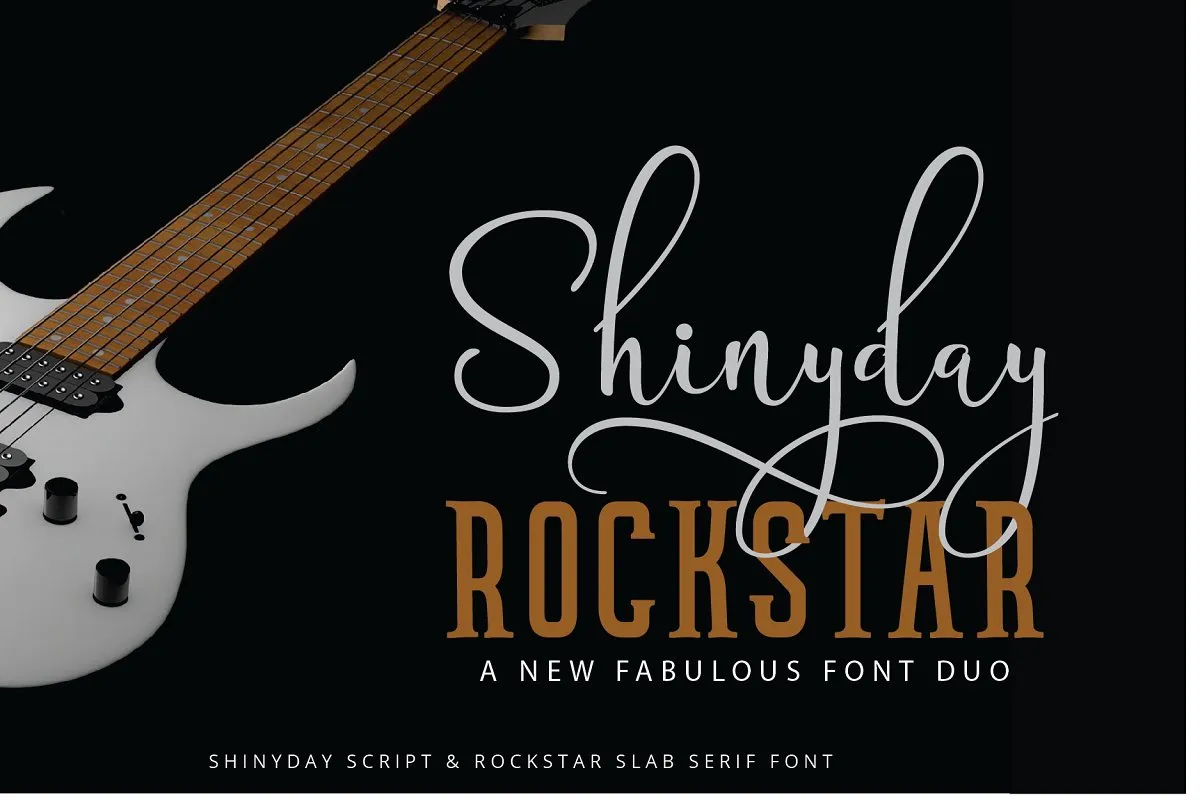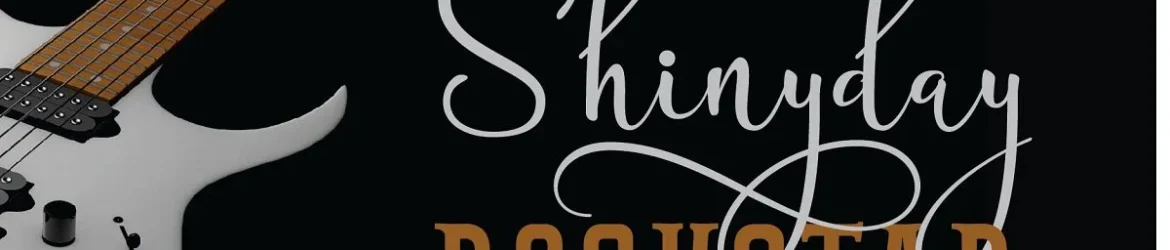
Shinyday & ROCKSTAR Font Duo – Download Grátis
A Shinyday & ROCKSTAR Font Duo é uma paixão para os amantes do design gráfico que buscam uma combinação única de elegância e modernidade. Shinyday, uma elegante font script com alternativas de estilo mais sofisticado, traz um ar feminino ao mesmo tempo em alta qualidade premium. Ela complementa perfeitamente o ROCKSTAR, uma fonte serif estreita que transmite força e vitalidade jovem, seu nome incluído. Esta dupla é ideada para aplicações como títulos, desenhos, panfletos, blog, temas femininos e girly, mídias sociais e marcas de empresas. É a combinação perfeita para quem valoriza sofisticação com uma pitada de espírito jovem.